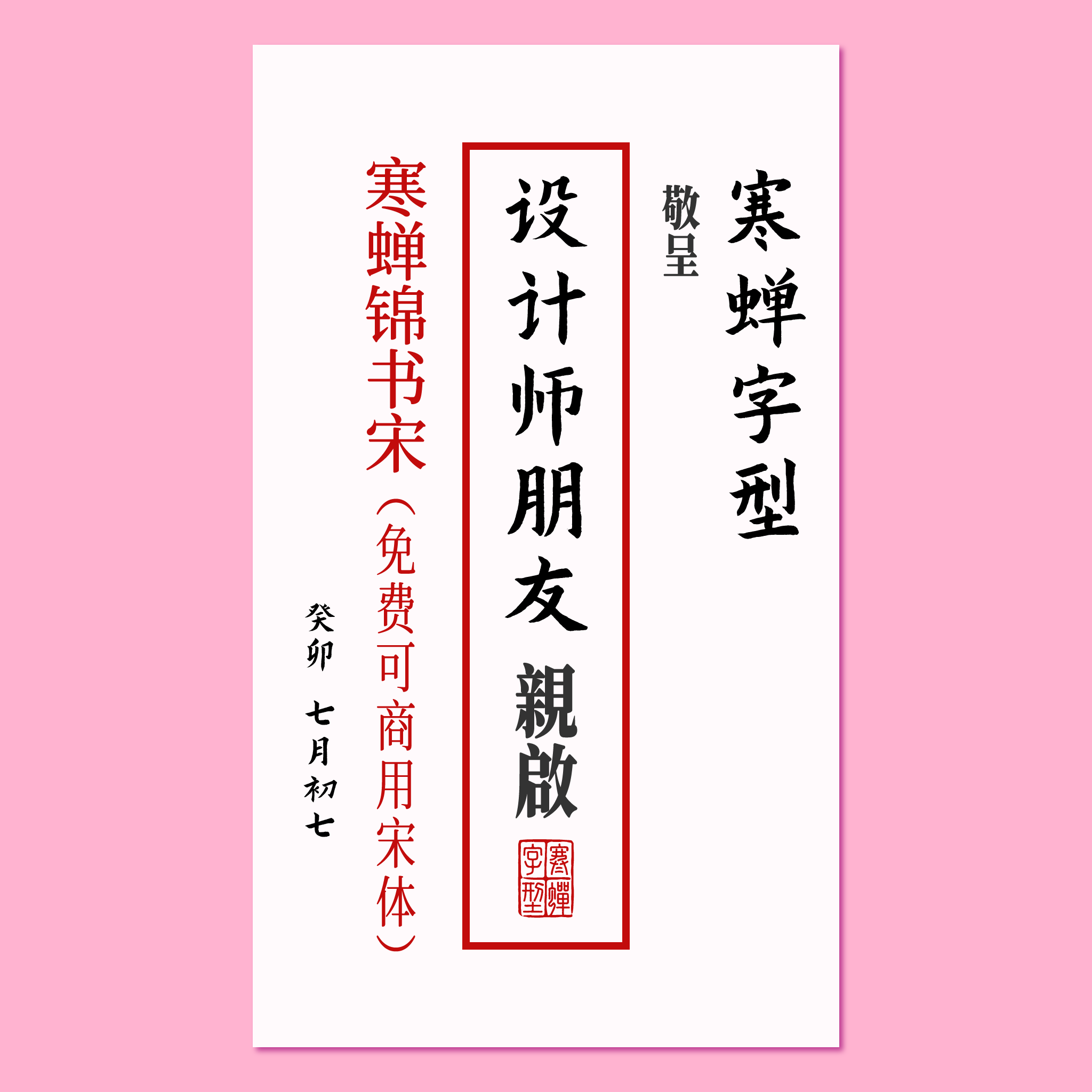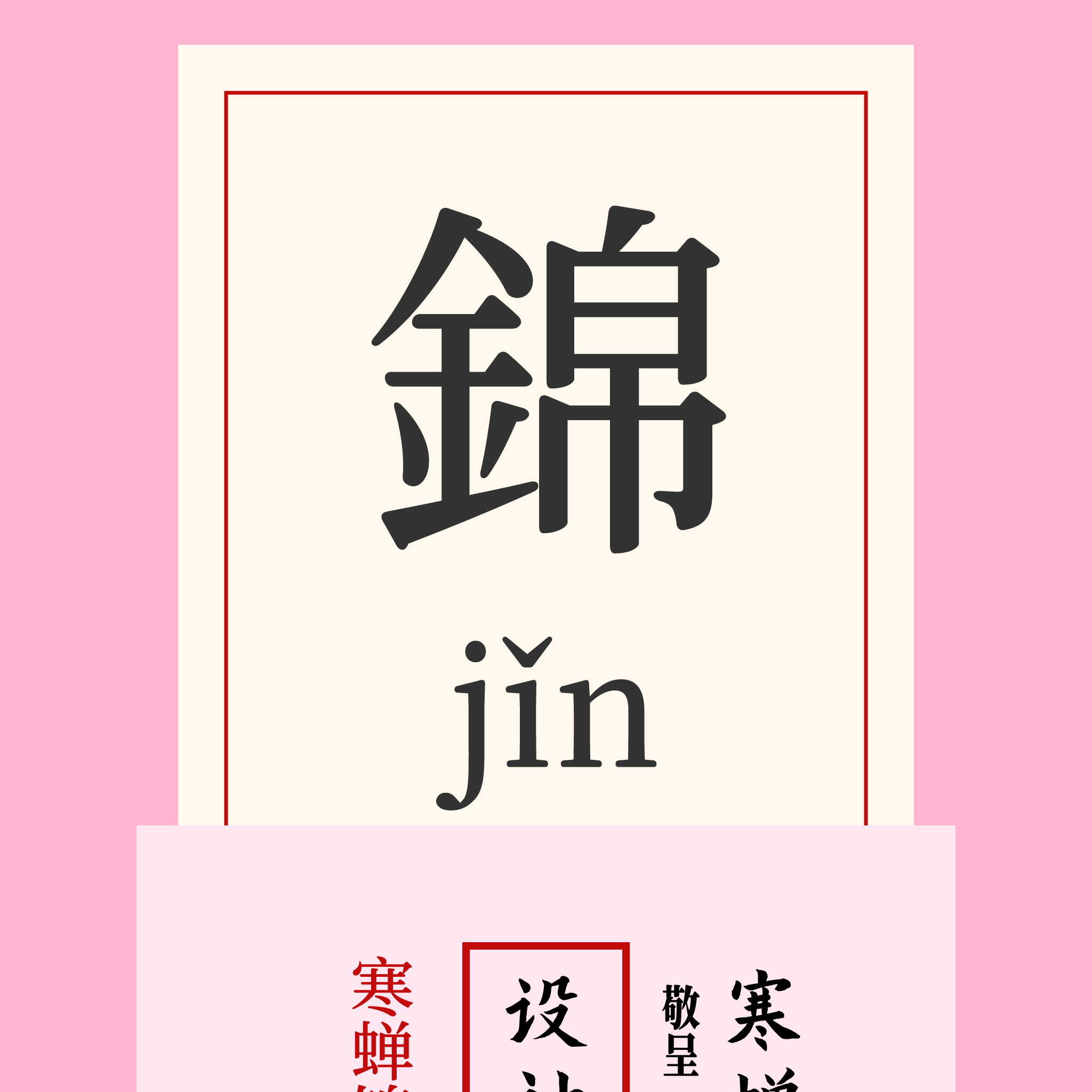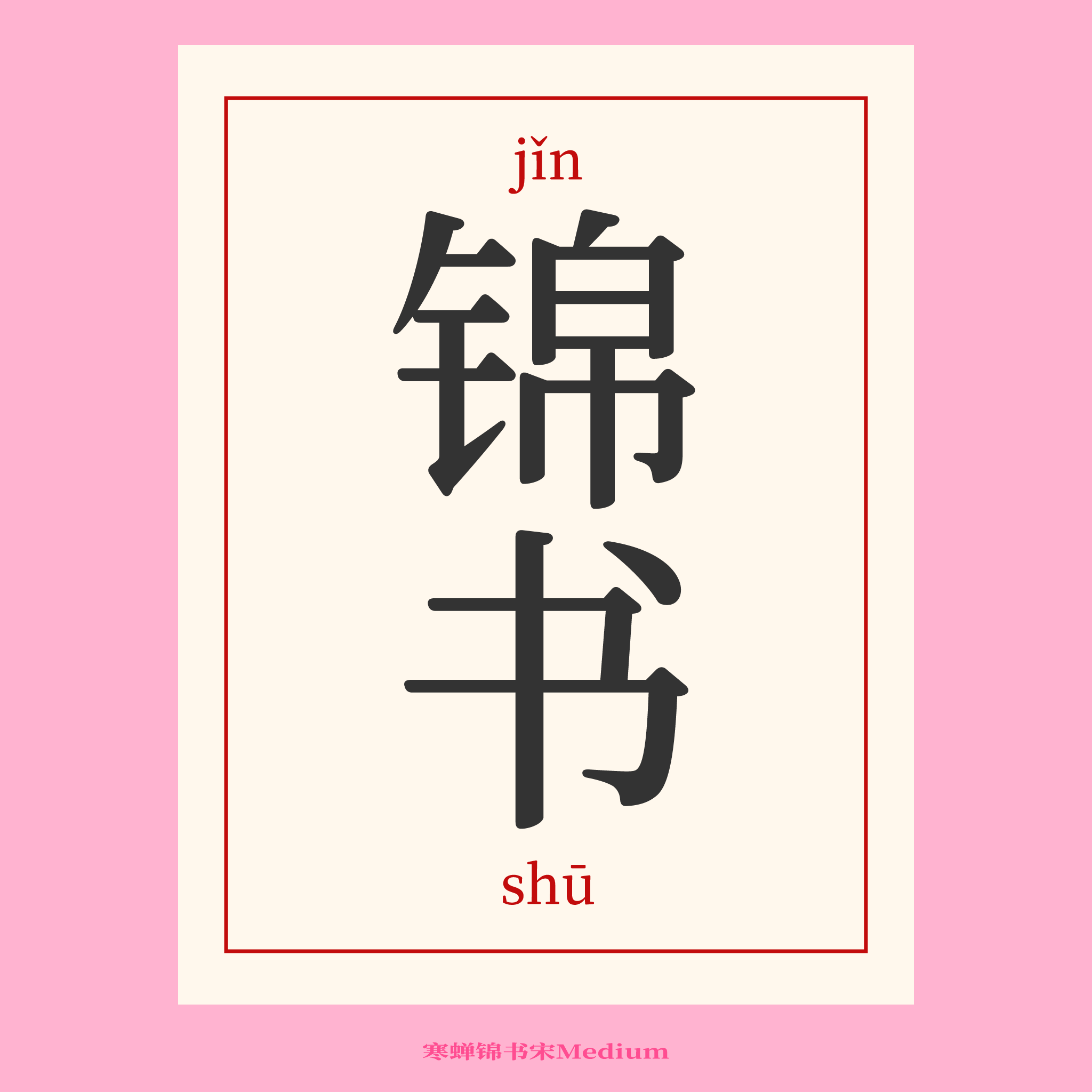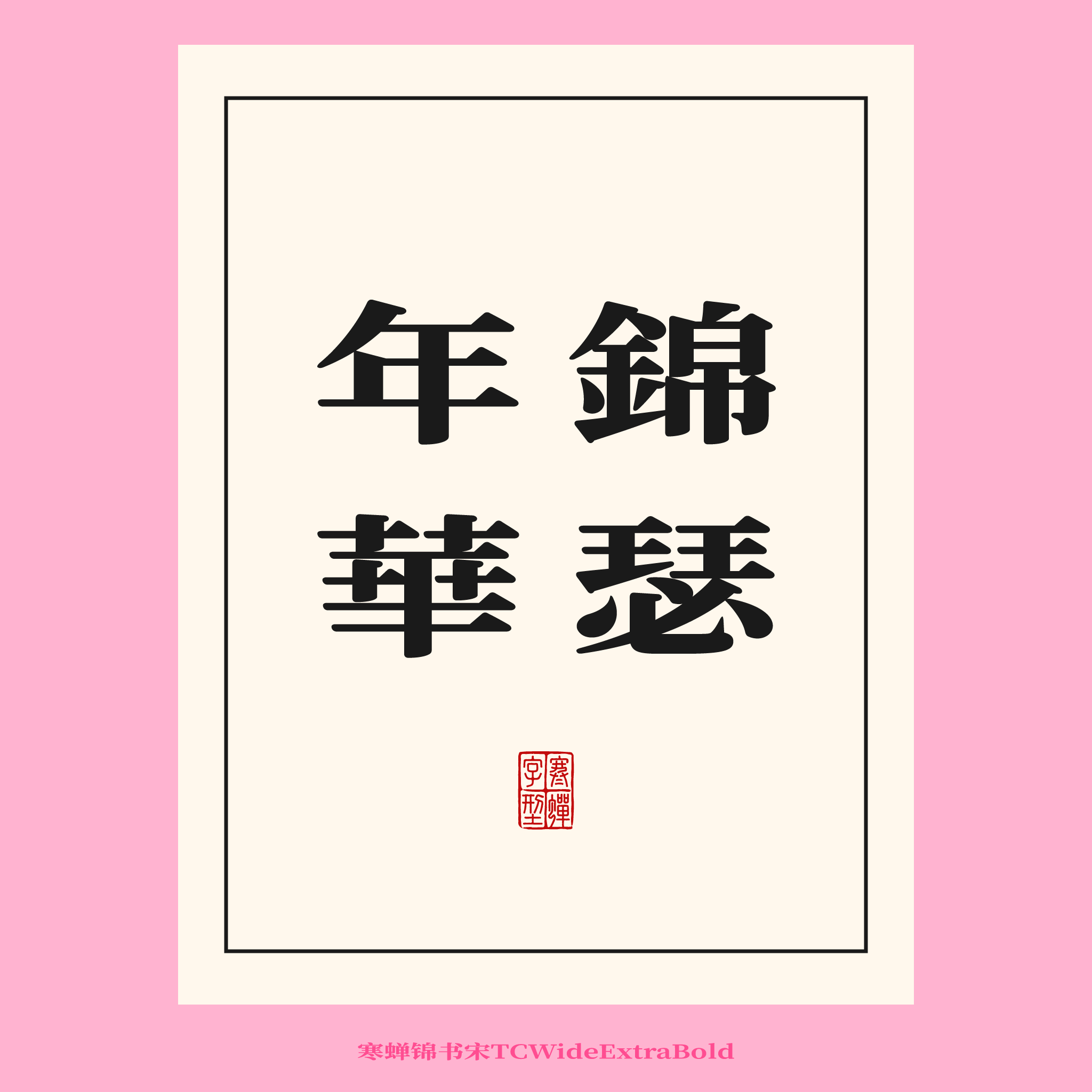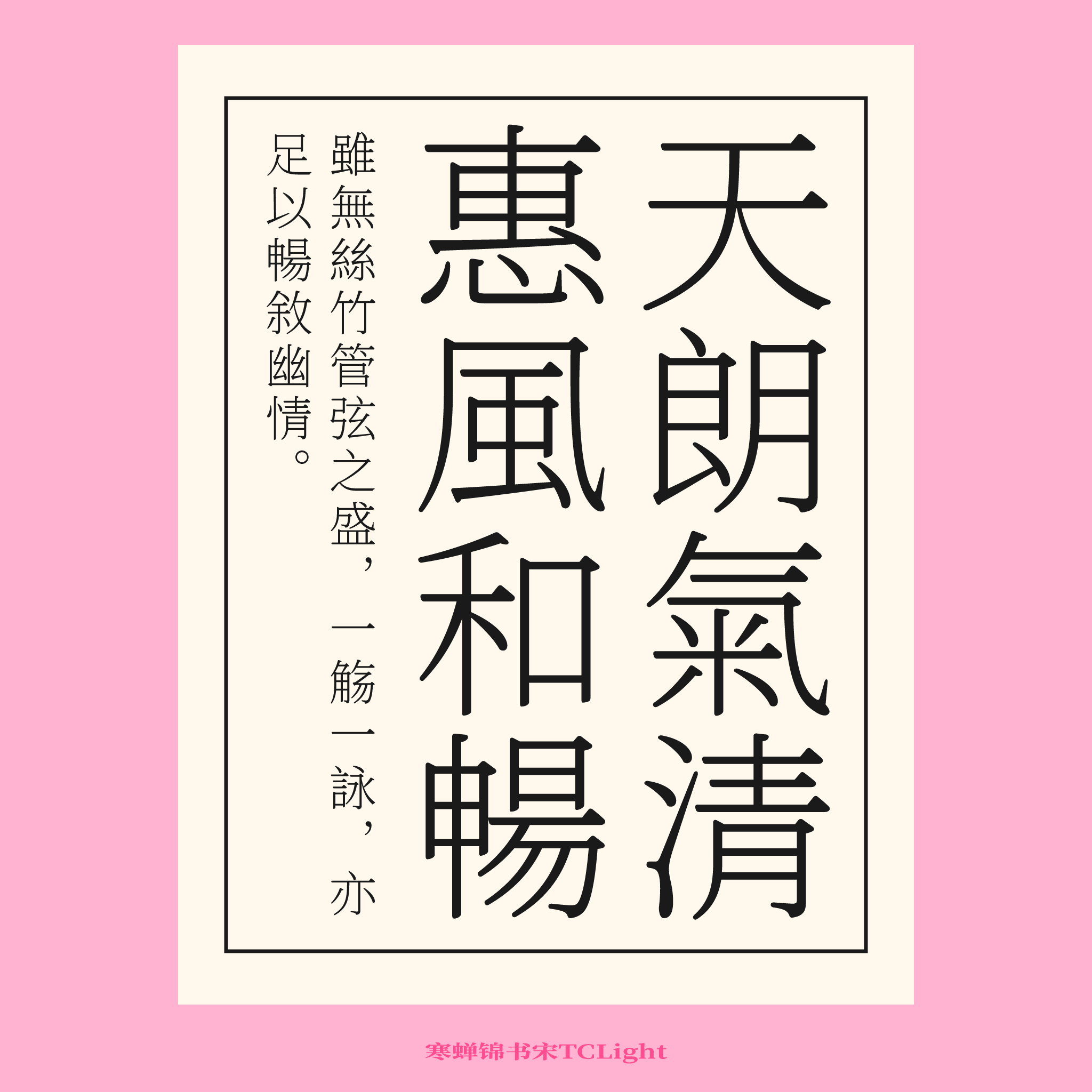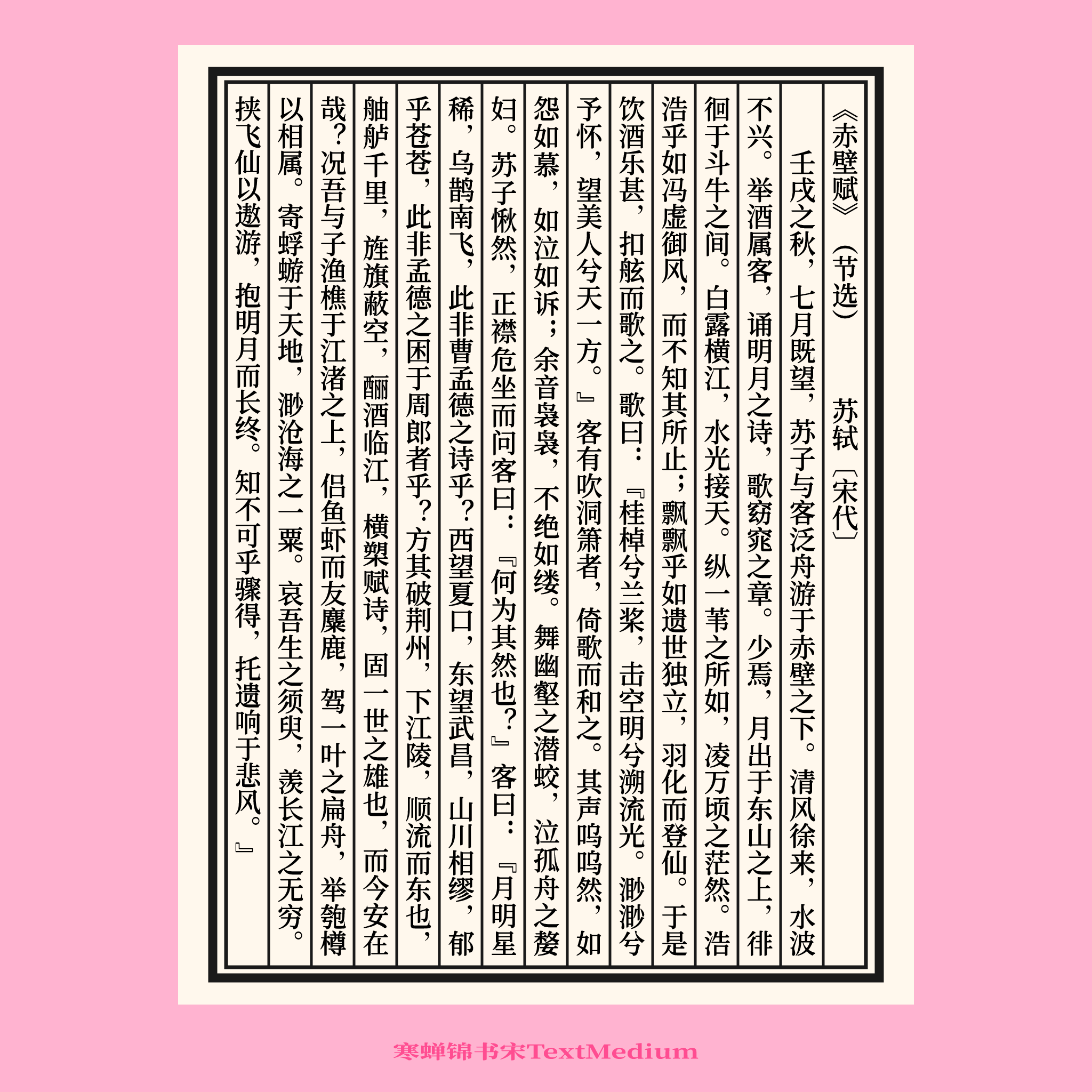
寒蝉锦书宋
寒蝉锦书宋(Chill Jinshu Song)是一款在思源宋体基础上融入圆角设计,旨在提供更温润、均衡阅读体验的开源中文字体。该字体以 Adobe 与 Google 联合开发的思源宋体(Source Han Serif)为蓝本进行深度修改。其核心优化在于为传统宋体锋利的笔画转折与末端添加了统一的圆角处理,从而显著软化了视觉观感,使字体整体气质更为柔和、亲切。
同时字体对排版细节进行了优化,并重构了字重比例,使各字重之间的粗细过渡更加平滑均衡,提升了长篇阅读的舒适度。其名称“锦书”蕴含“锦上添花”与“前程似锦”的双关美意,寄托了美好愿景。
字体风格
寒蝉锦书宋在保留了思源宋体清晰、严谨骨架结构的同时,通过关键的“圆角化”处理,实现了风格的微妙转型。所有笔画的起笔、收笔、转折处的锐利棱角都被柔和的圆弧所取代,这一设计消解了传统印刷宋体常有的冷峻感和机械感,为字体注入了手写般的温度与包容性。
经过重构的字重比例使得从细到粗的各级字重灰度均匀,版面效果扎实而平稳。这种“圆角宋体”的创意,在维持字体高可读性的前提下,营造出一种独特的人文关怀氛围,使文字界面显得友好、精致而不失庄重,恰如其名,实现了对经典宋体的“锦上添花”。